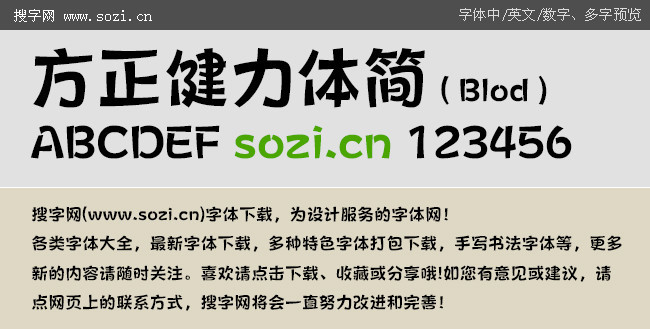
方正健力體簡(jiǎn)Blod
搜字網(wǎng)提供一款方正健力體簡(jiǎn)中文字體下載,方正健力體是作者從某健身的標(biāo)志引發(fā)的靈感,點(diǎn),撇,捺,抅,橫,直劃等都是不同方向,也好像各種健身項(xiàng)目的不同表達(dá)方式一樣,是一款充滿動(dòng)感和活力的字體。適合健美行業(yè),活力飲料,運(yùn)動(dòng)服裝和運(yùn)動(dòng)鞋的廣告宣傳。